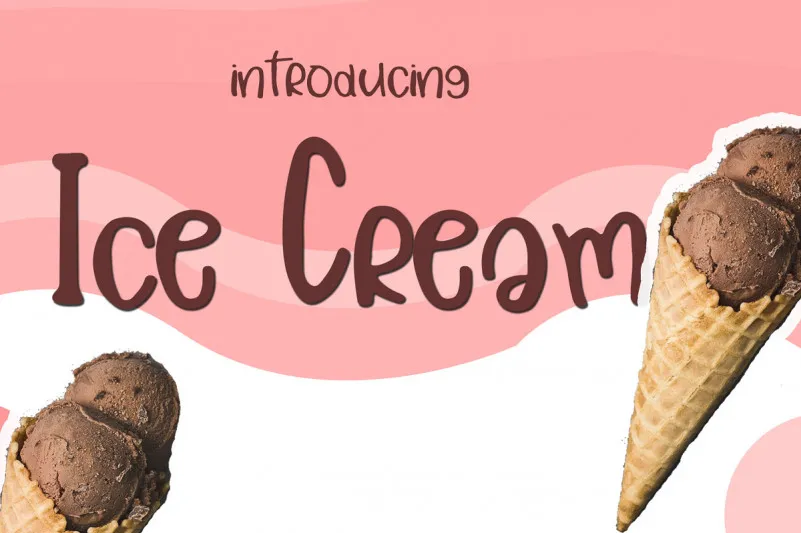
Ice Cream Font
A fonte Ice Cream Font é perfeitamente indicada para ambientes infantis e temáticas de doces que requerem uma pitada de descontração e criatividade. Desenvolvida pelo designer Genarastudio, essa elegante fonte cuidadosamente escrita em caligrafia está repleta da suavidade e relaxamento que combina perfeitamente com temas infantis. Suas características criativas tornam-a perfeita para projetos como rascunhos de crianças, desenhos animados ou até mesmo ilustrações de doces congelados. Quando combinada com cores vivas e alegres, sua abordagem descontraída se traduz em experiências visualmente estimulantes e divertidas, tornando-a uma escolha ideal para designers buscando trazer um toque especial a seus projetos infantis.